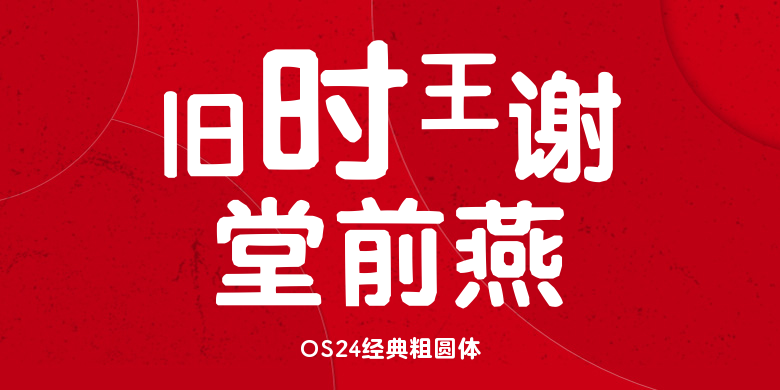
OS24经典粗圆体
OS24经典粗圆体,这款字体结构工整、笔画清晰,兼顾美观与易读性,适用于标题、正文、海报、包装、LOGO 等多种场景。字形优雅稳定,风格百搭耐看,适配日常排版与创意设计,让文字呈现更舒适、更具质感。OS24经典粗圆体一笔一画,皆是细节,以均衡的比例、流畅的线条打造舒适视觉体验,字形端正大气,风格简约现代。无论是商业设计、品牌宣传还是日常排版,都能轻松驾驭,让文字更有格调与力量。OS24经典粗圆体字体下载。